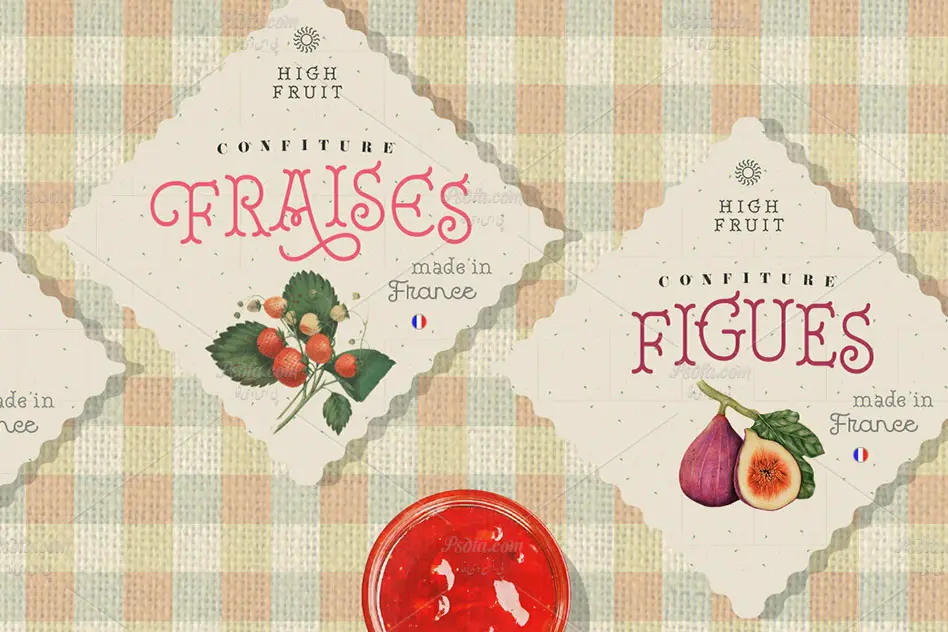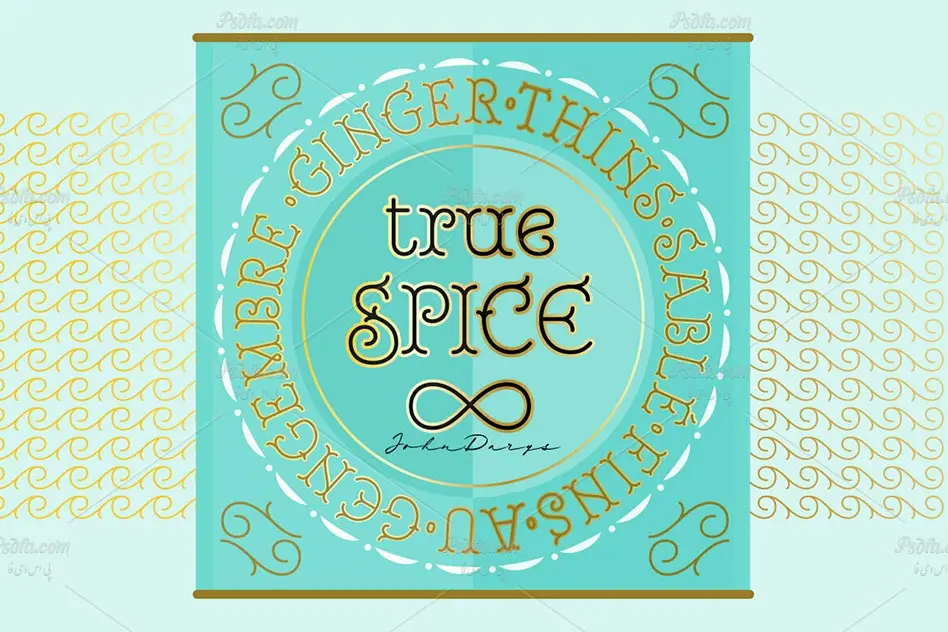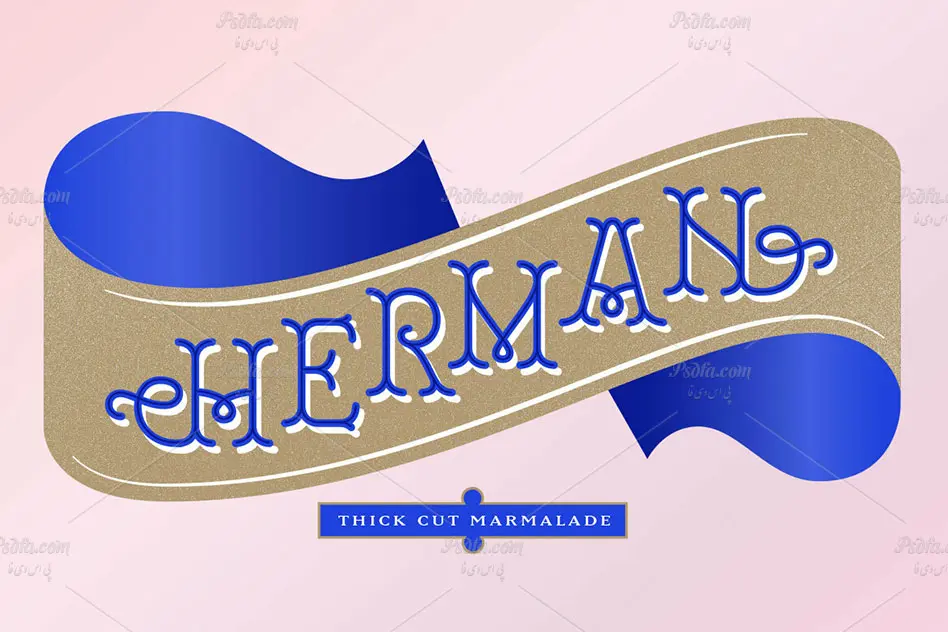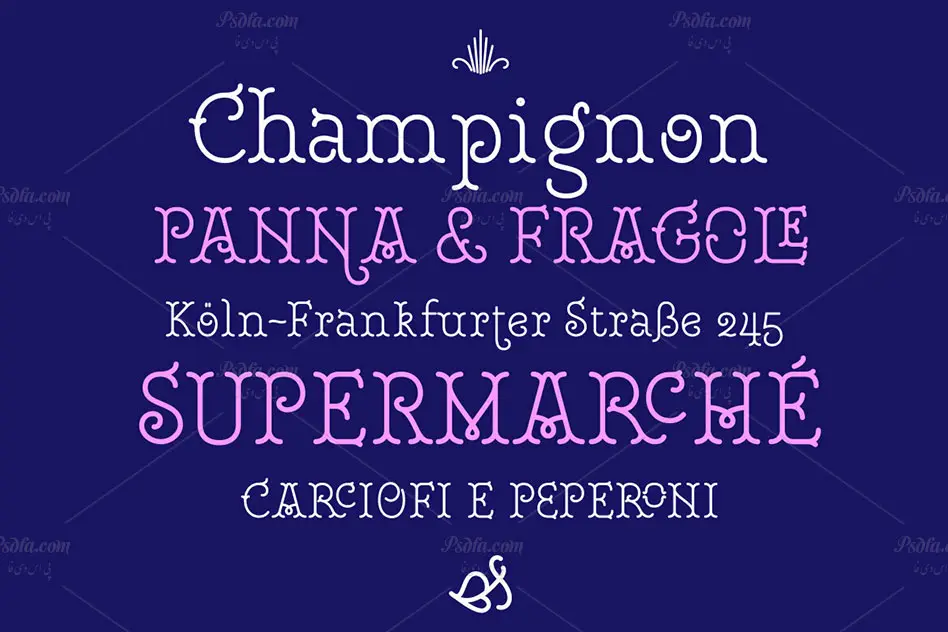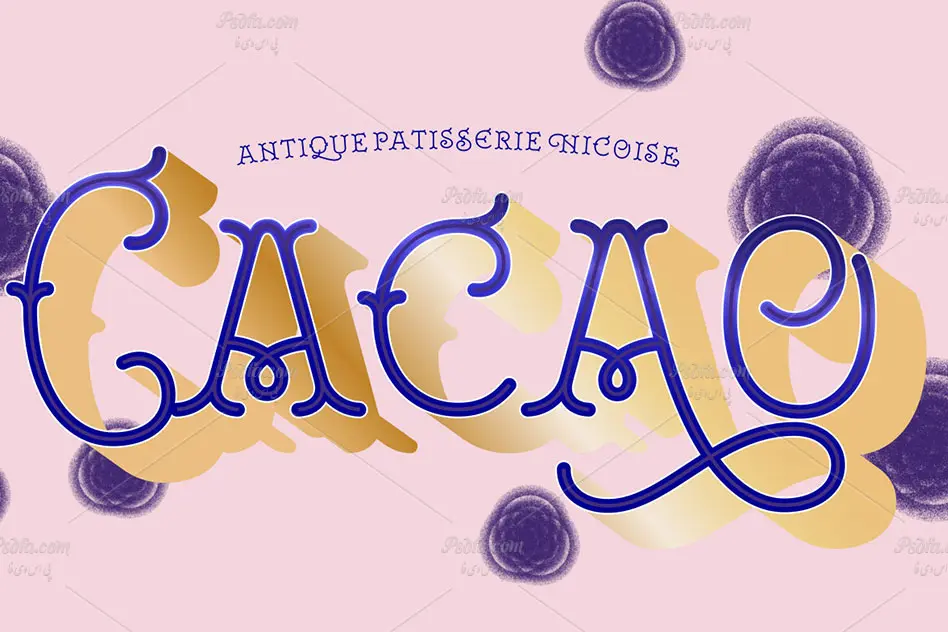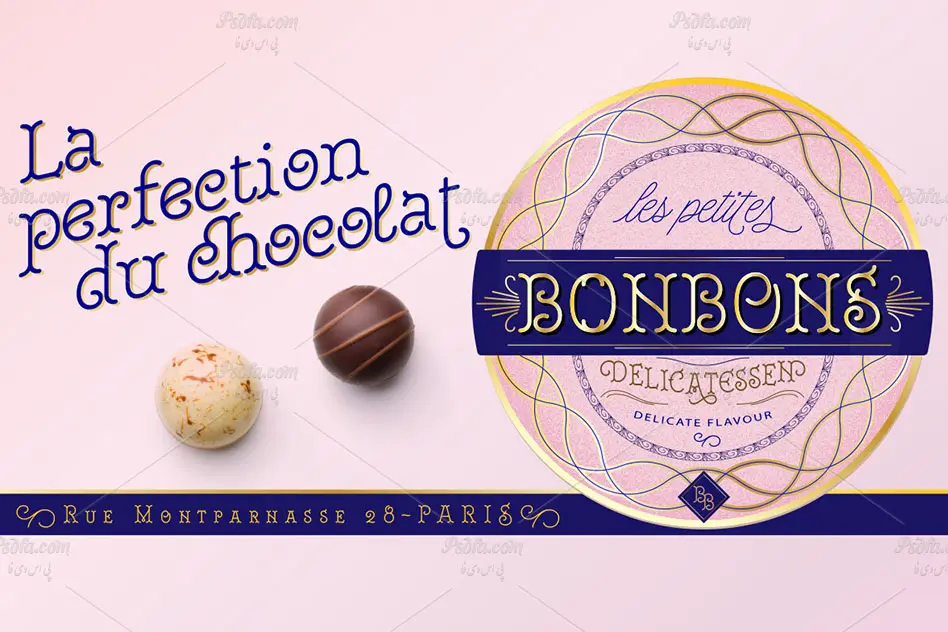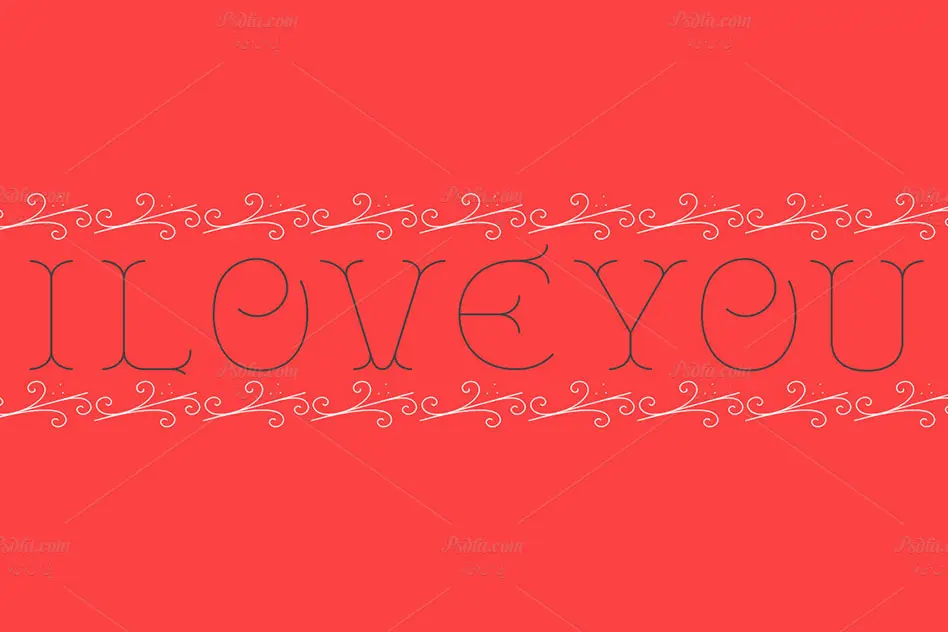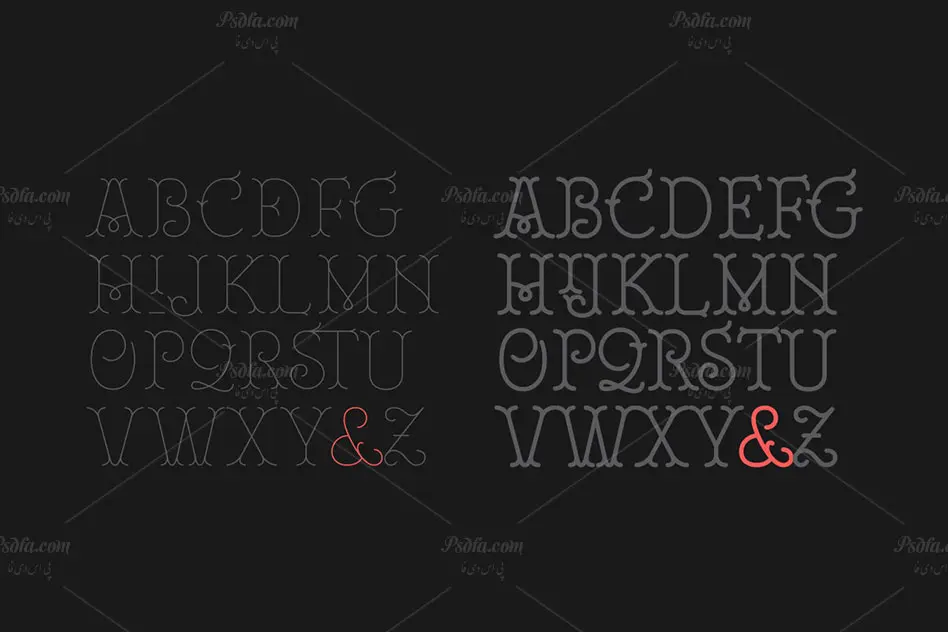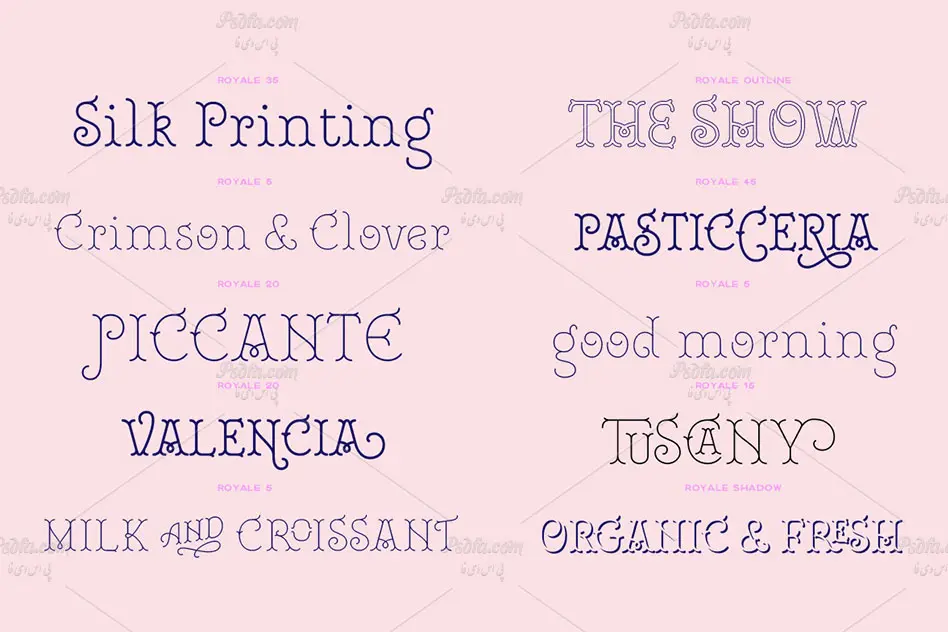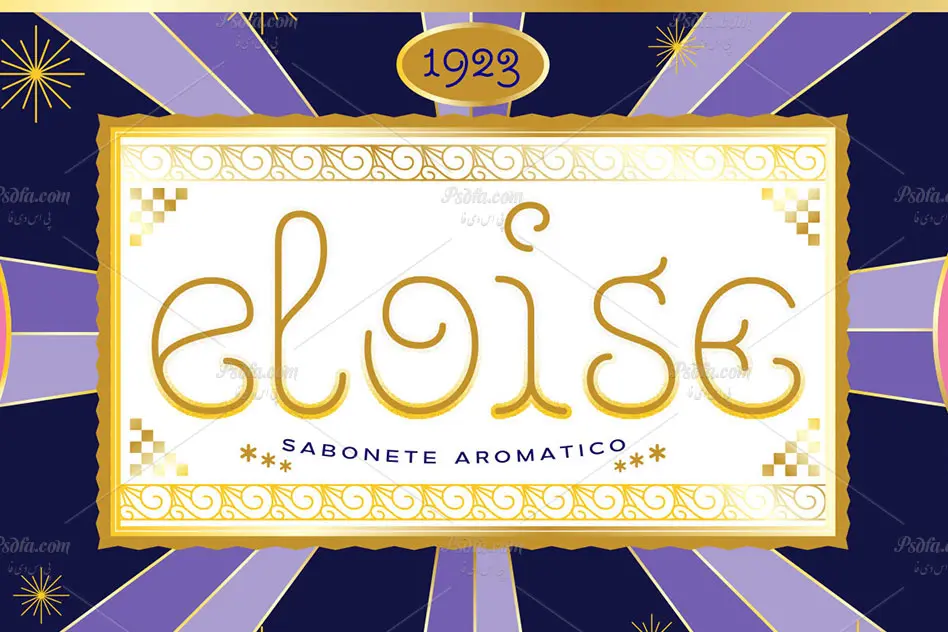
در این مطلب شاهد فونت انگلیسی طرح دار رویال Royale Font Family مناسب جهت استفاده در طرح های گرافیکی می باشید. خانواده فونت رویال شامل 36 فونت طرح دار فوق العاده زیبا در سبک و وزن های مختلف است که در قالب فایل های ttf بر روی سایت بارگذاری شده اند. با نصب این مجموعه فایل در پوشه فونت های سیستم قادر به استفاده از آن ها در تمام نرم افزارهای گرافیکی و ویرایشگر متن از جمله نرم افزار فتوشاپ ، افترافکت ، مجموعه نرم افزار آفیس و … خواهید بود. همانطور که ذکر شد فونت Royale در وزن و طرح های های مختلفی طراحی شده است که می توانید از آن در طراحی انواع طرح های گرافیکی همچون طراحی کارت ویزیت ، تراکت ، بروشور ، بنر ، انواع پوستر و … استفاده کنید.